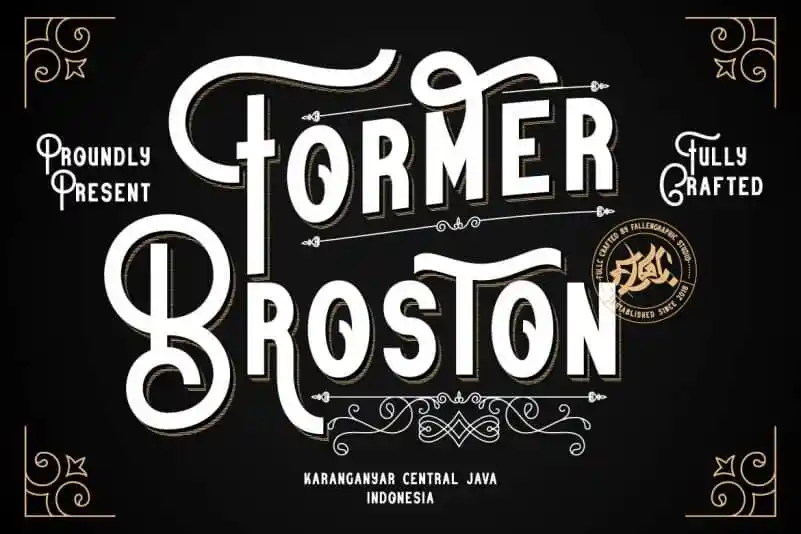
Former Broston Display Font – Download Grátis
A fonte “Former Broston Display Font” é uma seleção única no mundo dos tipos de letra, inspirada na forma geométrica sem serifas mas com uma aparência elegante e curvilínea. Especialmente indicada para apresentações ou logomarcas, esta fonte traz um conjunto diversificado de alternativas que asseguram sua personalidade única e destacada. Através da sua combinação de formas simples e fluidas com elementos sofisticados, a “Former Broston Display Font” oferece uma opção ideal para vários usos. Seja ela utilizada em estilos de marca, cabeçalhos, selos, logotipos, blog, convites de casamento, camisetas, cartões de visita, produtos promocionais, sinalização, rótulos, publicações, panfletas ou etiquetas, a fonte captura o espírito da apresentação e do design. A fonte “Former Broston Display Font” é perfeita para quem busca criar um toque diferenciado em qualquer projeto gráfico. Ela oferece a oportunidade de transformar simples textos em elementos vibrantes e memoráveis, que chamam a atenção dos espectadores e marcaram uma presença forte no design visual.